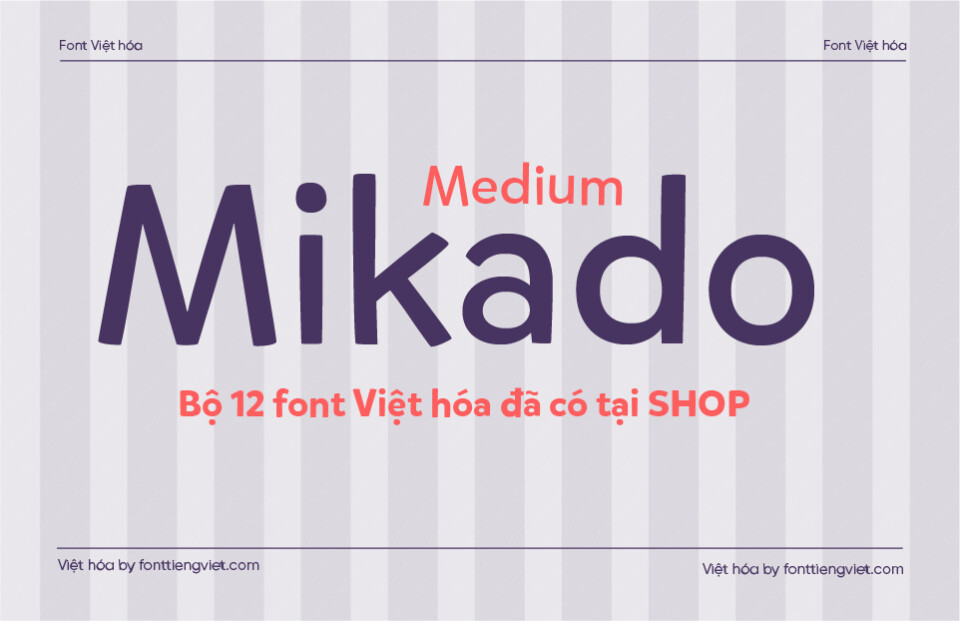
Font Việt hóa 1FTV VIP Mikado Medium
Giới thiệu về Font Việt hóa 1FTV VIP Mikado Medium
Trong thế giới đồ họa hiện đại, việc lựa chọn một bộ Font Miễn Phí chất lượng là yếu tố then chốt để tạo nên sự khác biệt. Font Việt hóa 1FTV VIP Mikado Medium nổi bật như một giải pháp hoàn hảo cho những ai đang tìm kiếm sự kết hợp giữa tính thân thiện và vẻ ngoài chuyên nghiệp. Đây là một phông chữ thuộc phong cách sans-serif nhưng được cách điệu với những đường cong mềm mại, mang lại cảm giác vui tươi, tràn đầy năng lượng nhưng vẫn đảm bảo sự cân bằng và dễ đọc trên nhiều nền tảng khác nhau.
Đặc điểm nổi bật của Font Việt hóa 1FTV VIP Mikado Medium
Thiết kế tối ưu và linh hoạt
Đặc điểm ấn tượng nhất của Font Việt hóa 1FTV VIP Mikado Medium chính là cấu trúc ký tự tròn trịa và hiện đại. Phông chữ này không chỉ phù hợp cho các tiêu đề quảng cáo, bìa sách mà còn cực kỳ hiệu quả khi ứng dụng trong thiết kế giao diện ứng dụng hoặc website giáo dục. Với độ dày Medium vừa phải, bộ font này giúp nội dung trở nên thanh thoát, không gây cảm giác nặng nề cho người xem, từ đó nâng cao trải nghiệm thị giác một cách tự nhiên nhất.
Khả năng tương thích hoàn hảo
Khi sử dụng Font Việt hóa 1FTV VIP Mikado Medium, người dùng hoàn toàn có thể yên tâm về khả năng hiển thị tiếng Việt. Từng dấu thanh và ký tự đặc trưng đều được căn chỉnh tỉ mỉ, giúp loại bỏ lỗi hiển thị phổ biến trong thiết kế Việt. Điều này đặc biệt hữu ích cho các bạn học sinh và giáo viên khi soạn thảo giáo án điện tử hoặc làm bài thuyết trình sinh động.
Kết luận và trải nghiệm Font Việt hóa 1FTV VIP Mikado Medium